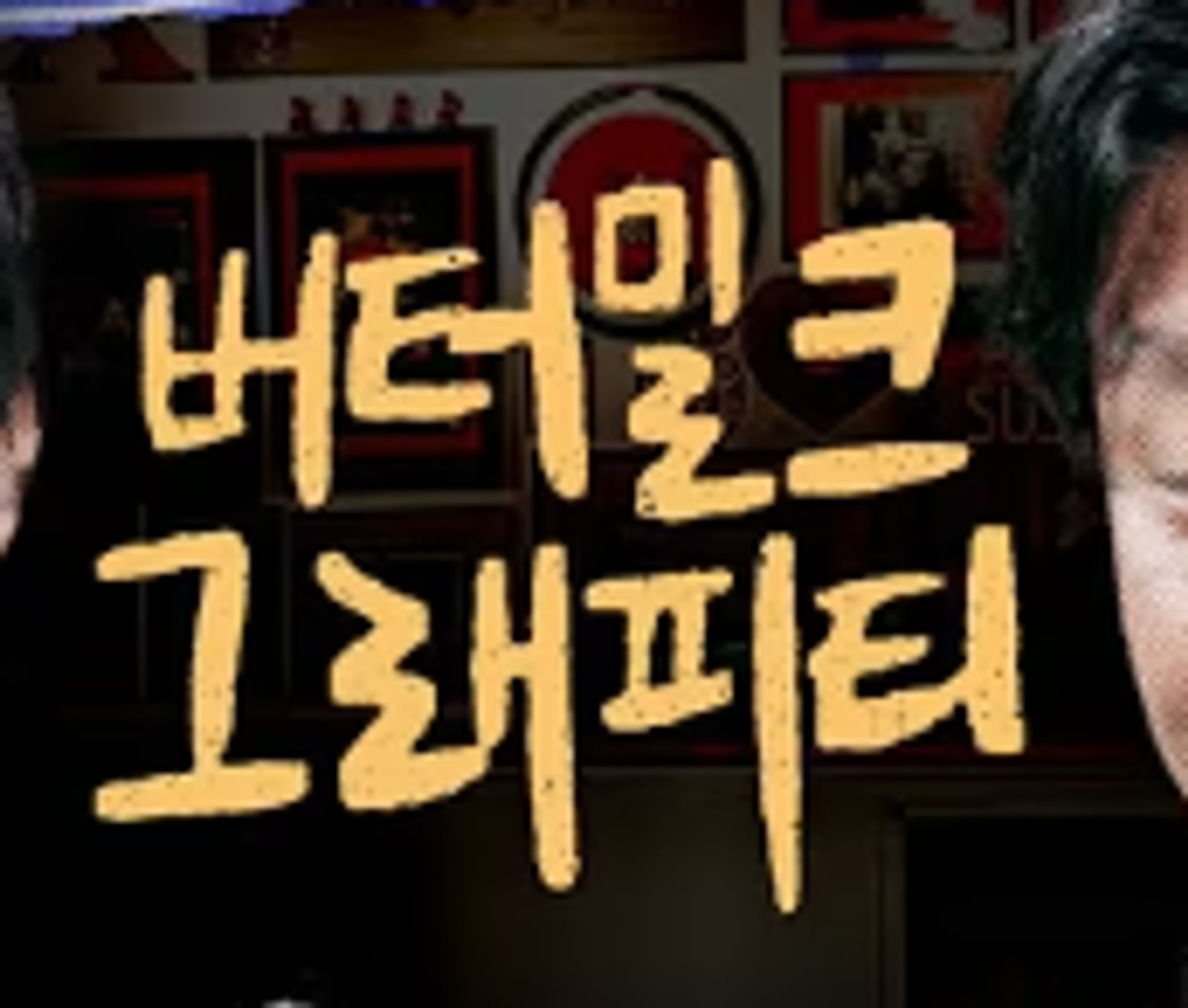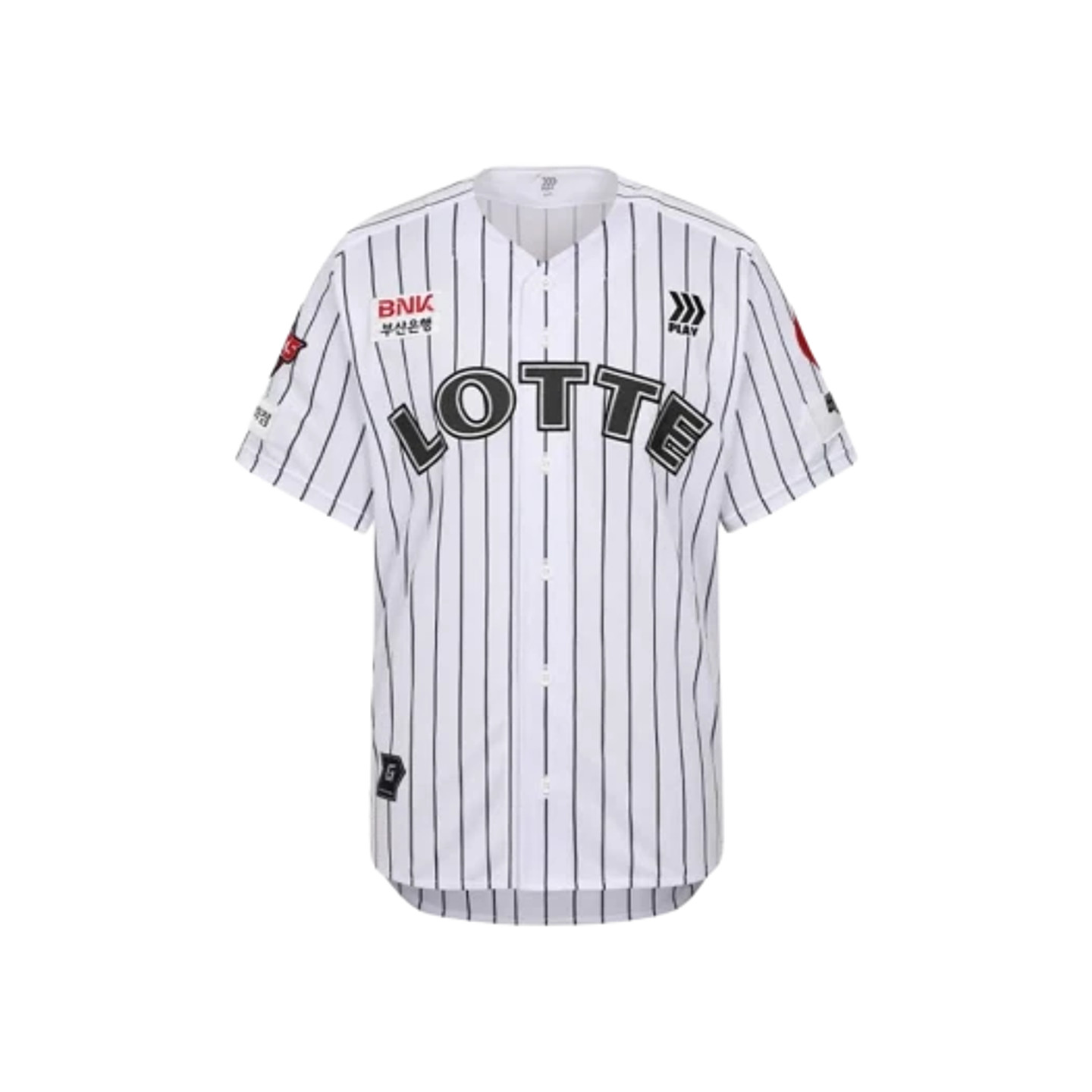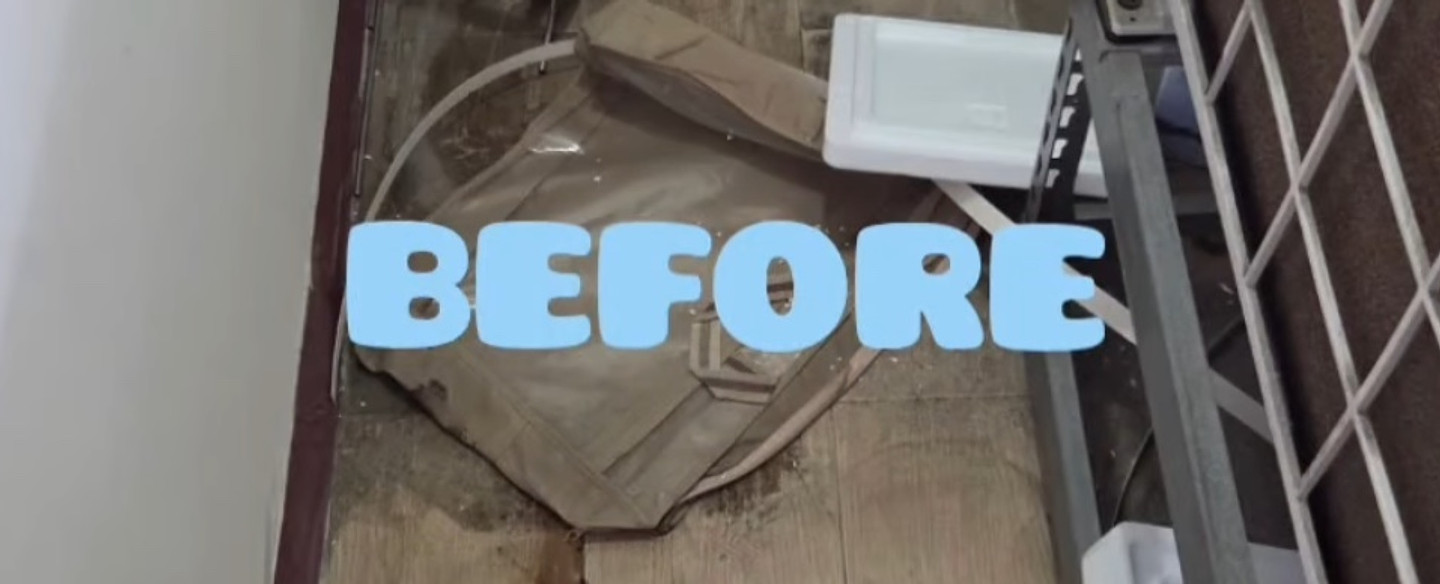
이 폰트 알고 싶어요 비슷한 폰트도 있는 지 알고 싶어용ㅠ
폰트가 궁금합니다. 한글 부분은 산돌 다솔과 비슷하긴 한데 세부 비율이 다르네요. 영문 폰트도 동일한건지 아님 기타 폰트인지 궁금합니다
폰트명을 알고 싶어요?
이게 무슨 폰트 일까요?
혹시 이 폰트가 뭔지 아시는 분이 계실까요? ㅠㅠ
요 폰트 너무 궁금해요 미리 감사합니다
게시글에서 본 글꼴인데 아무리 찾아도 모르겠네요..
폰트 이름이 뭘까요??
이 폰트 뭔지 아시는분...🥺
한글
붗글씨로 흘려쓴 글씨체
이 폰트가 궁금합니다람쥐
이 사진들 나와 있는 폰트 전부 무슨 폰트인가요!?
이 사진들 나와 있는 폰트 무슨 폰트인가요!?
이 사진에 나와 있는 폰트 전부 무슨 폰트인가요!?
이 이미지 속 폰트 대체 뭘까요???? 쓰고 싶은데 뭔지를 몰라서 진짜 답답해요ㅠㅠ
이거 혹시 무슨 폰트일가요? 정확한 폰트이름 찾기 힘들다면, 근접한 폰트라도 추천부탁드립니다!
글씨체가뭔지
이게 무슨서체일까요...?
희망두배청년통장 폰트가 궁금해요
버블 말풍선 속 폰트 제벌 찾아주세요 ㅜㅜ
안녕하세용. 이 폰트 궁금해요 미리 감사합니다
하얀색으로 설명적혀있는 폰트 제발 어떤건지 아시는분 찾습니다!
큰 글씨 폰트가 어떤걸까요?ㅠㅠ
이 글꼴 이름이 뭔가요ㅠㅠ
무슨폰트인가요ㅜㅠ!!
무슨 글씨체인지 궁금합니다!
숫자랑 영문 폰트 두가지 궁금해요ㅠㅠ!
폰트 이름 궁금해요~
알쓸신잡 유튜브에 나오는 자막인데 무슨 폰트에요?
이 폰트 뭘까요??ㅠㅠ
위에 폰트랑 밑에 폰트 알려주실 수 있을까요?
폰트 아시는 분 있을까요
무슨폰트일까요??
말풍선 폰트 뭔지 궁금해용... 유료 폰트 중에 있을꺼 같은ㄷㅔ ㅠㅠㅠ
중심 타이틀 조구만 꽃가게의 폰트와 위아래 꾸불한 손글씨 폰트 알 수 있을까요?
혹시 이 로고에 사용된 폰트 알 수 있을까요?
무슨 폰트인지 알수 있을까요?
혹시 이거 폰트 아시는분ㅠㅠ?
이 한글 폰트 알 수 있을까요?
기본 폰트인거같은데ㅠㅠ
이 폰트 뭘까요 ? HNT 브로콜리친구들 TTF Bold 는 아닙니다..
폰트 정보 궁금합니다!
DMZ 폰트인데 무슨 폰트인지 궁금해요,,
위 아래 폰트 어떤 폰트일까용 ..!?? ㅠㅠㅠ 너무 궁금합니다
무슨폰트일까요~~ ㅜ
폰트 이름이 궁금합니다.
봄소풍 동영상 제목으로 쓰인 글꼴인데 이름을 알고 싶습니다.
무슨 폰트인지 알려주세요
아일릿 3월 31일에 업로드 된 밤소풍 릴스 폰트 궁금해요!!! 🌙🌃🔮
무슨 폰트일까요...!?
ppt 폰트 글씨체 뭔지 알 수 있을까요? ㅠ ㅠ 아무리 찾아봐도 알 수 가 없네요,,
폰트 알려주세요!
최근 브이로그에서 많이 쓰이는 자막 같은데 어떤 폰트인지 아시는 분 있을까요?
영문폰트 무슨 폰트인지 알 수 있을까요? ㅜㅠ
여기 하단에 설명으로 들어간 '현장학습으로 VR 체험관에 왔는데 하필 태하랑 유지호와 같은 팀이 되었다~~~' 이 폰트 뭘까요? ㅠ
메모먼트 꾹꾹체같은데 다운링크좀 뷰턱해요 ㅠㅠ 메모먼트 카톡을 1달 넘게 안보내요;;;